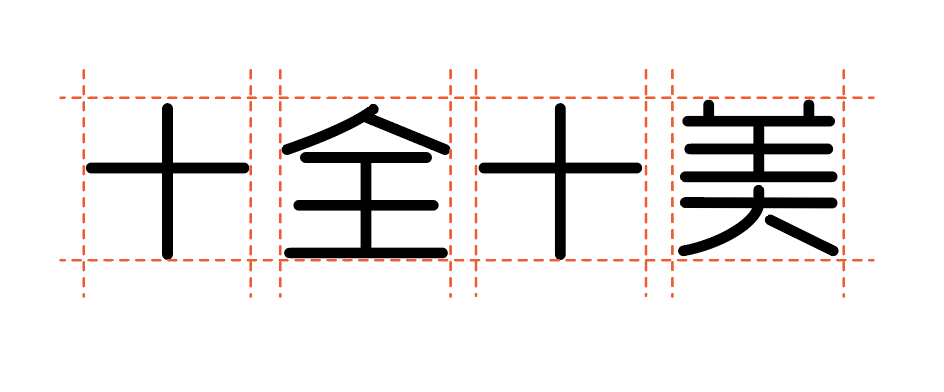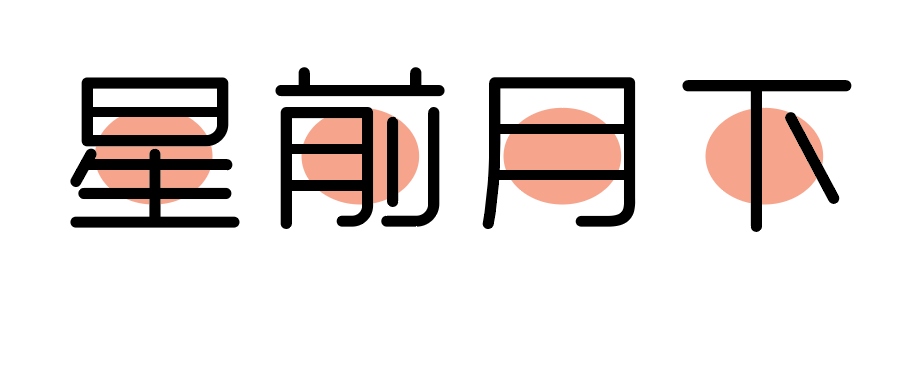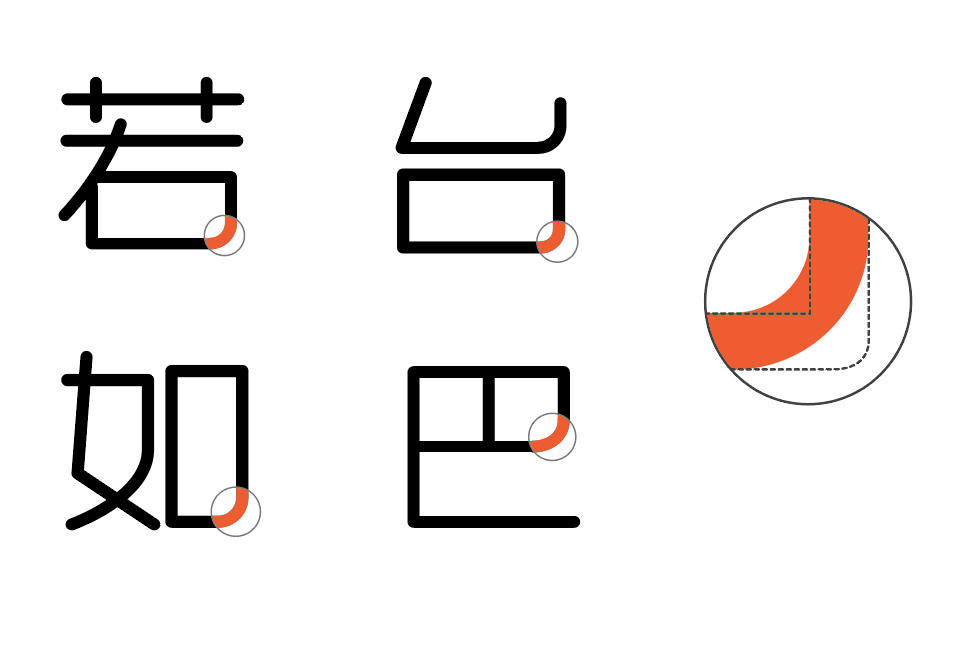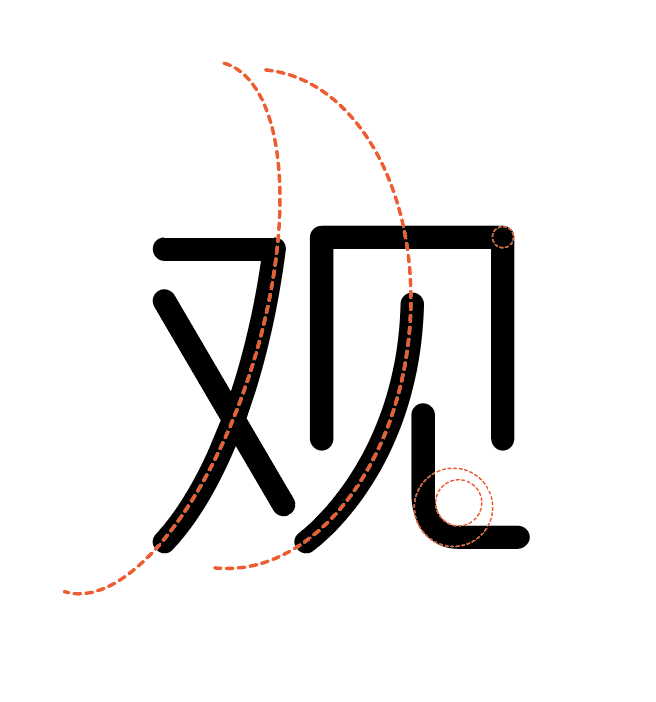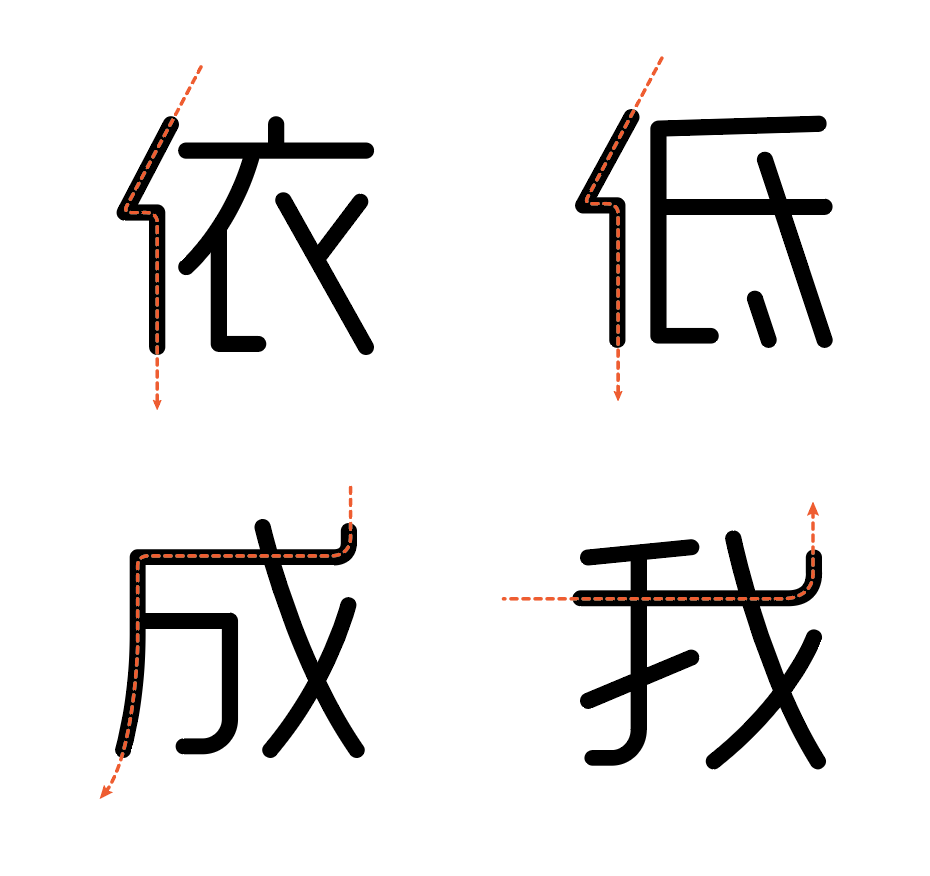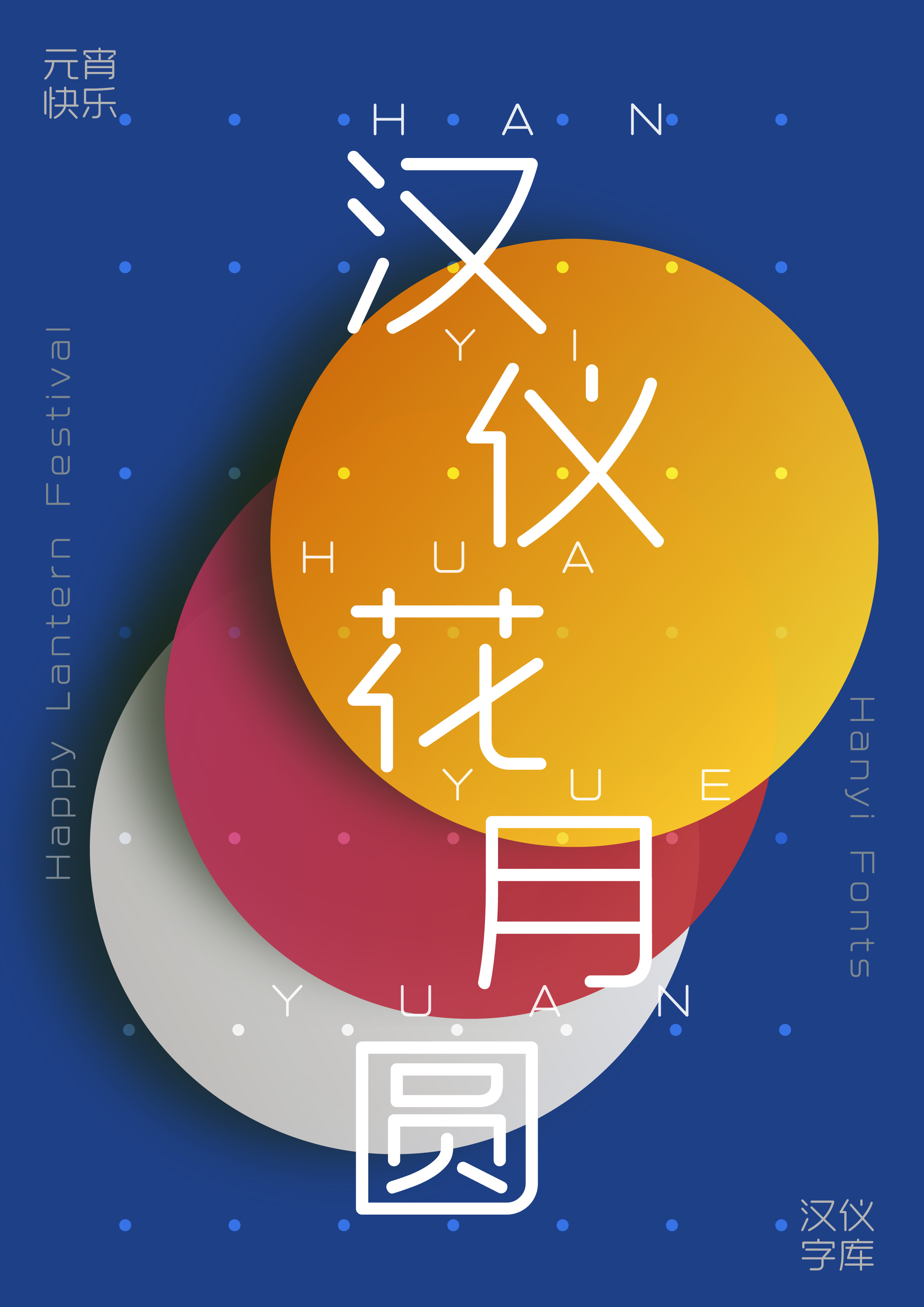
汉仪晓波花月圆字体介绍,一款时尚兼具女性性格特征的字体
汉仪晓波花月圆 | 字形特点
“汉仪晓波花月圆”是一款时尚兼具女性性格特征的字体。它字形便扁,重心较稳。有端庄大方,举止得体的女性仪态。是一款极具女性视觉语言的圆体。
汉仪晓波花月圆 | 中宫大小
“汉仪晓波花月圆”中宫略大,字形舒朗,气势浑圆饱满,体现着海纳百川,有容乃大的包容气度。
汉仪晓波花月圆 | 笔画特点
“汉仪晓波花月圆”笔画处理创新而巧妙,既避免了传统圆体的雷同处理效果,又增加了多重曲线感,使字体的女性美感呼之欲出。
汉仪晓波花月圆 | 曲线感
“汉仪晓波花月圆”行笔圆润,曲线感强,笔画之间尽显了多样而丰富的曲线,将女性的柔美表现的淋漓尽致。不禁赞叹设计师的独具匠心。
汉仪晓波花月圆 | 连笔特点
“汉仪晓波花月圆”采用连笔的方式简化了部分笔画,使字体更加简洁明快,线条清晰流畅,现代感增强。
汉仪晓波花月圆 | 案例展示
中文字体主创团队:胡晓波工作室
中文字体执行团队:字研工作室
西文字体主创设计师:张暄